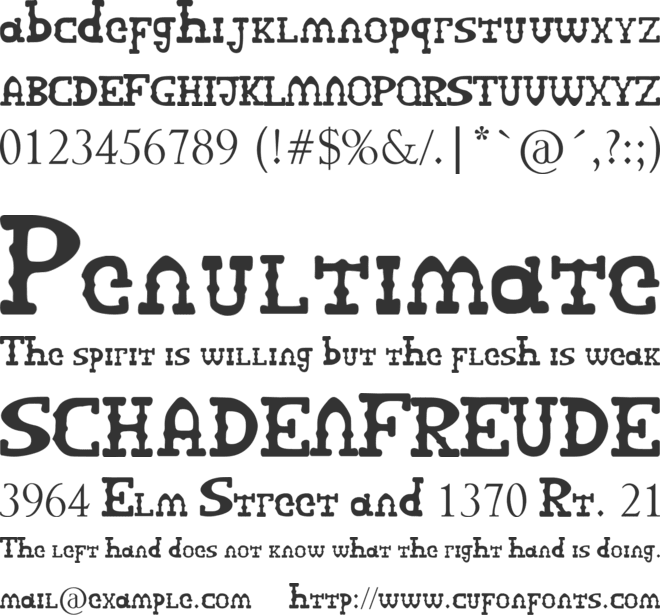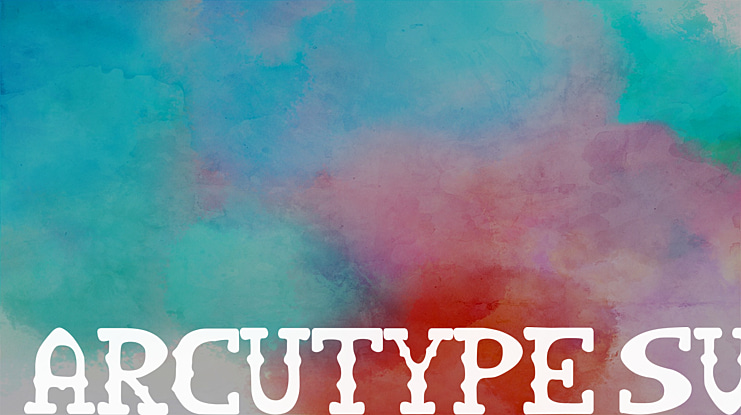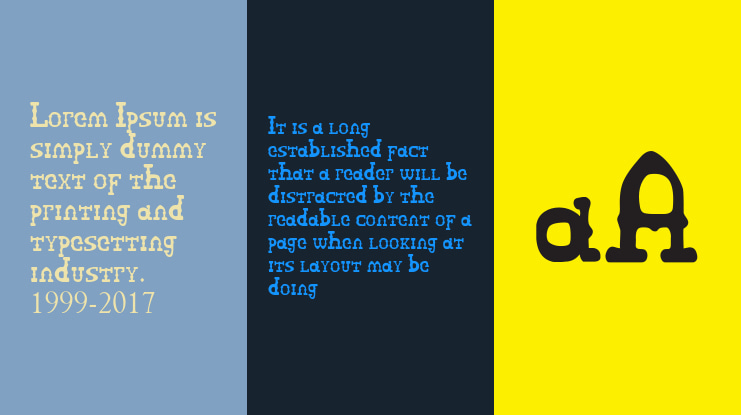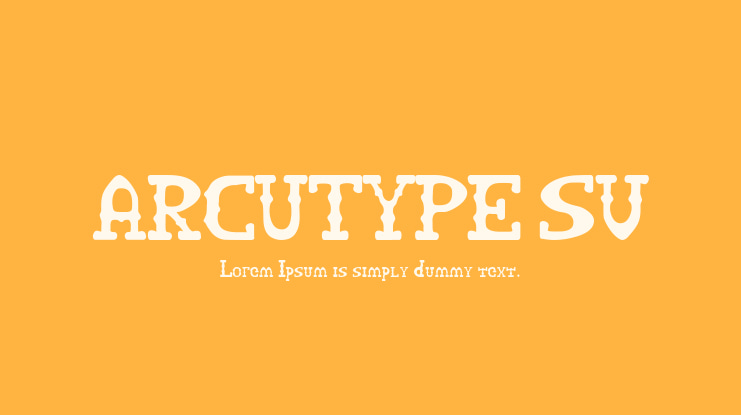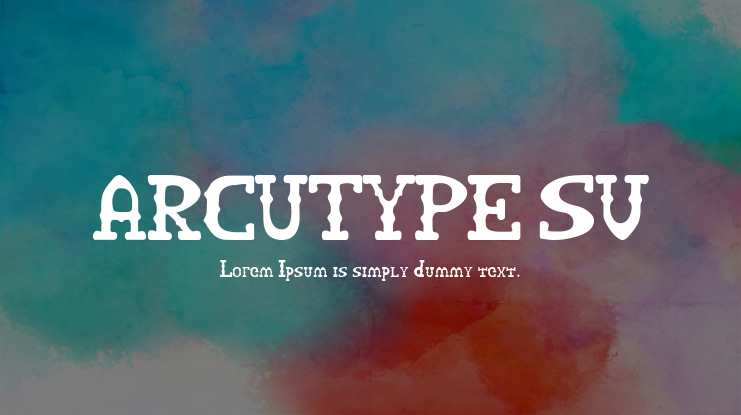
ARCUTYPE SV Font
Tipografía creada como examen parcial de la materia tipografía aplicada en la carrera de diseño gráfico por el alumno Kevin Salinas.
Tipografía basada en la arquitectura salvadoreña, pero más que todo en el uso de arcos de medio punto y ojivales, a la vez reflejando un poco de la cultura y la arquitectura del gran San Salvador.